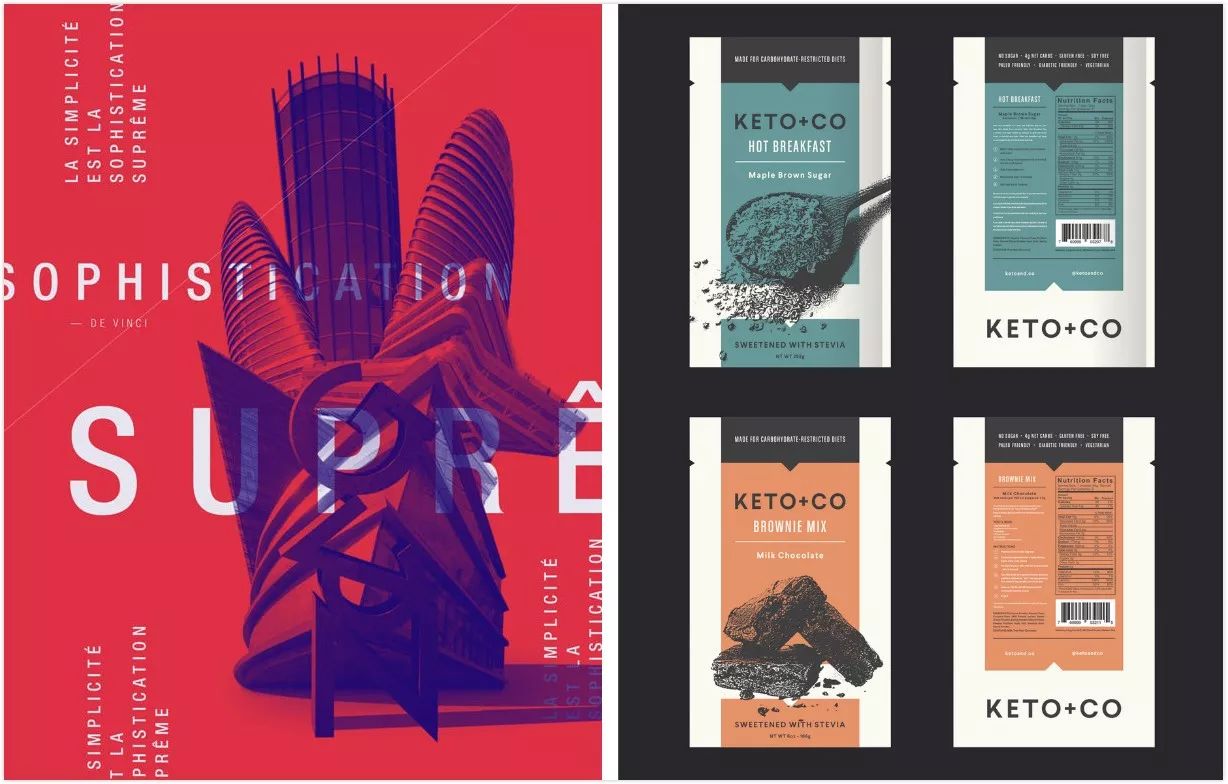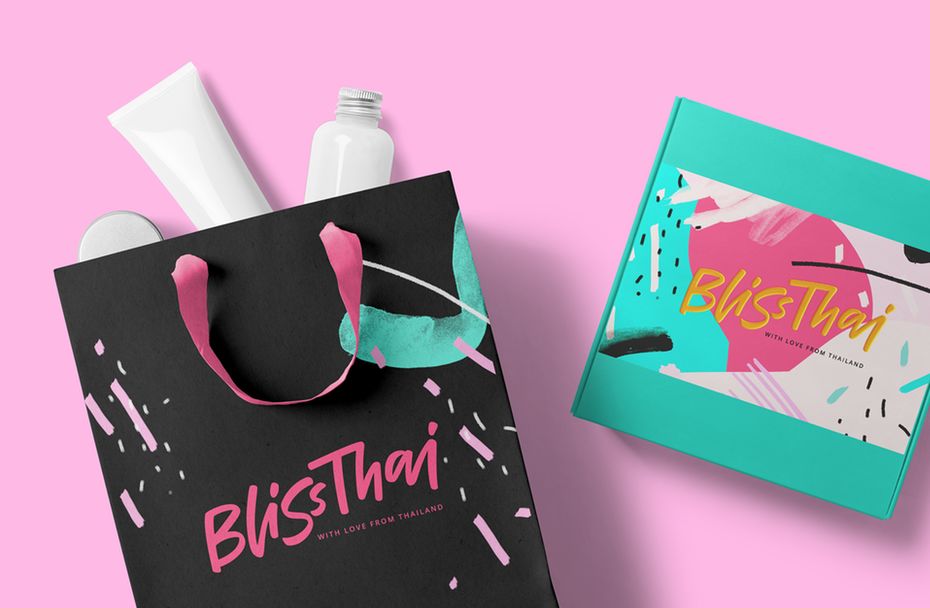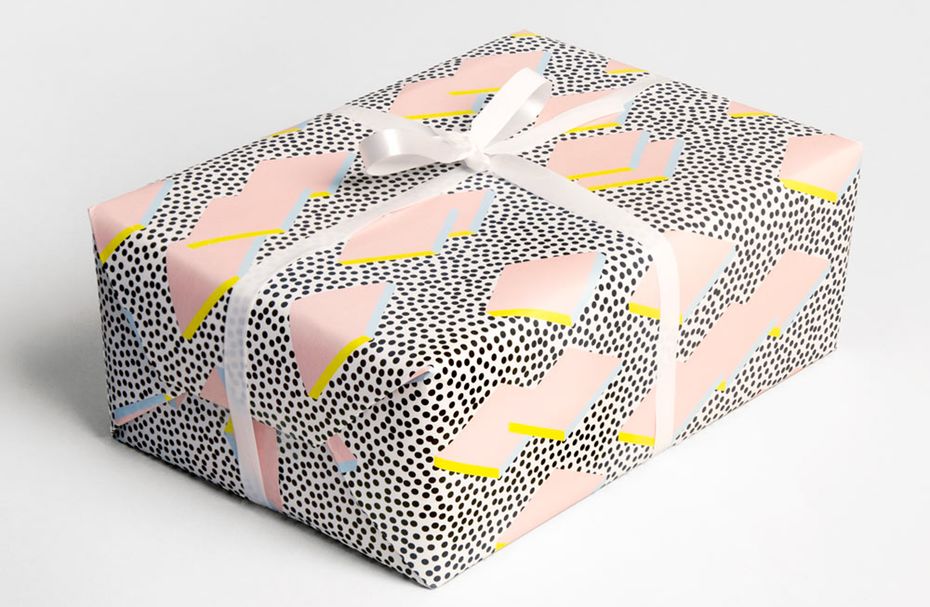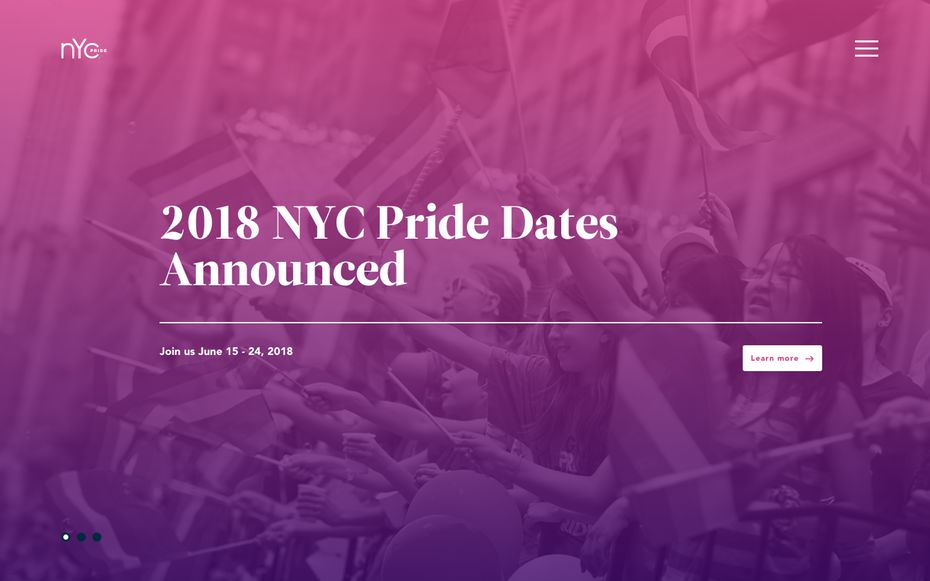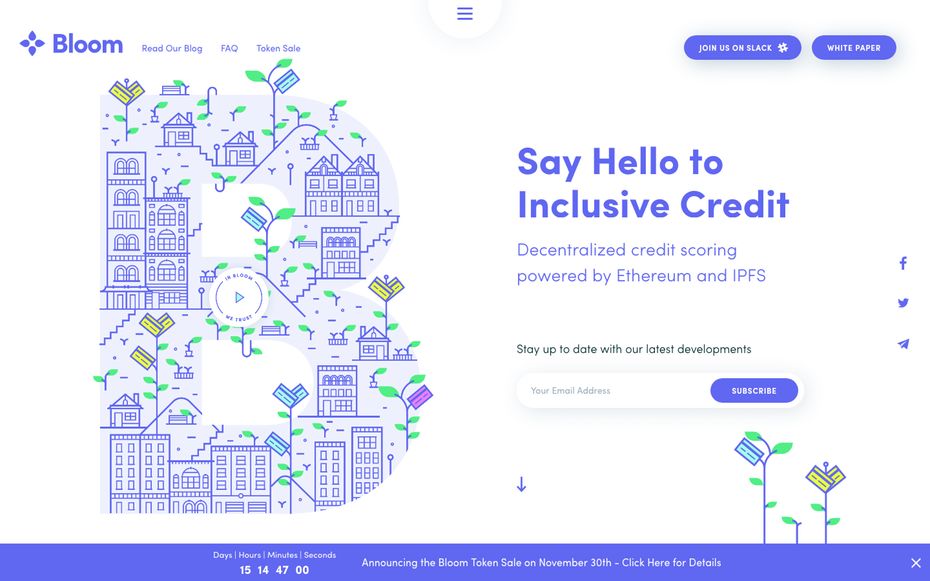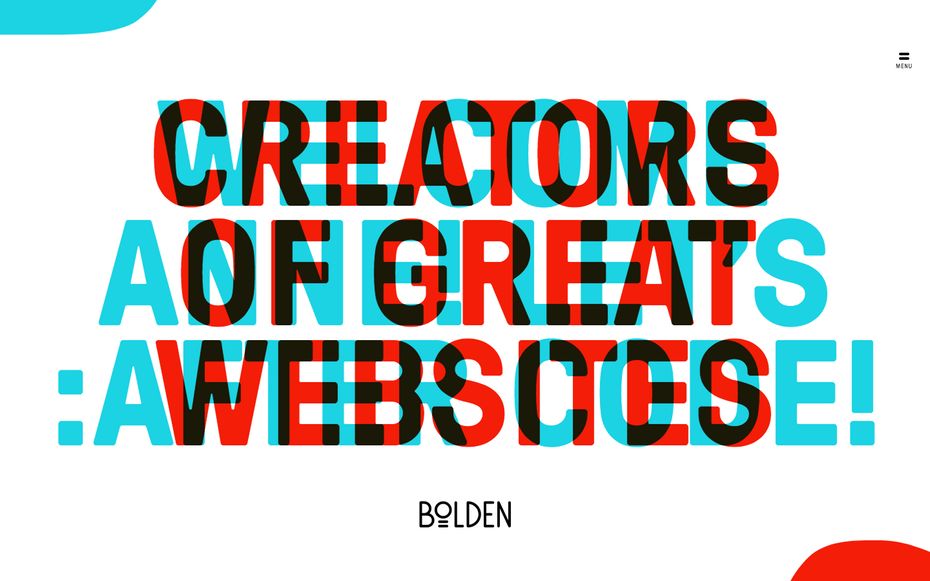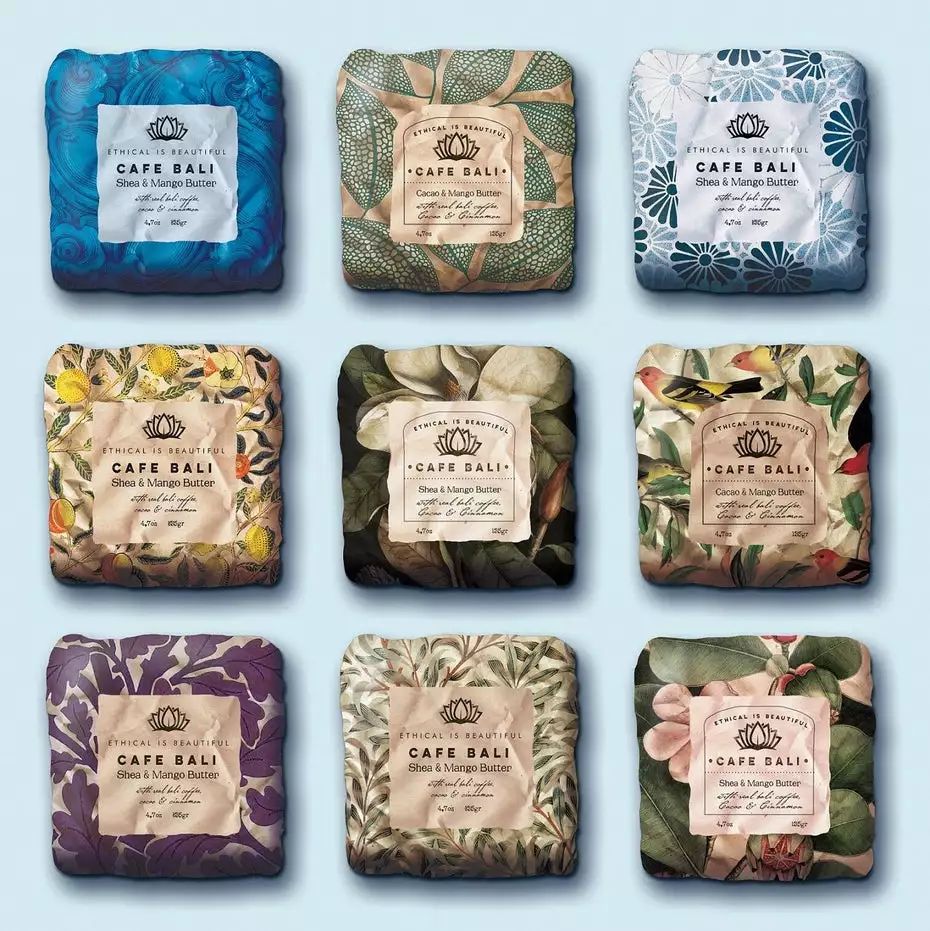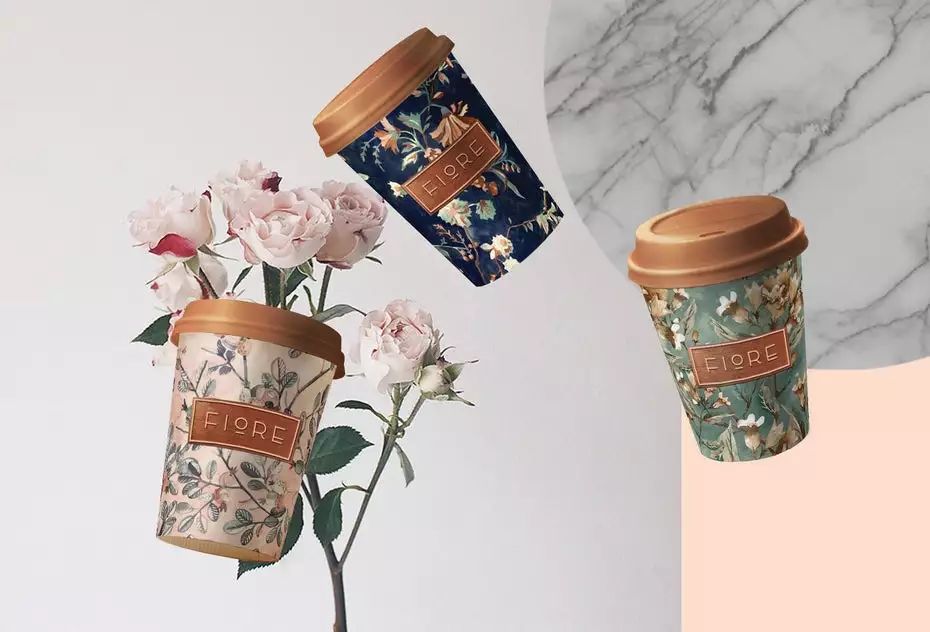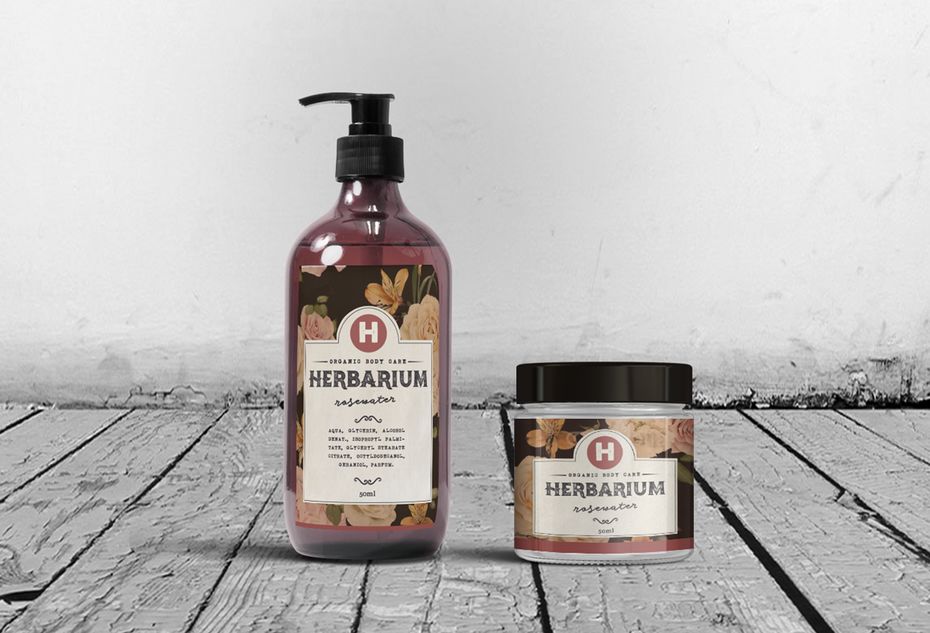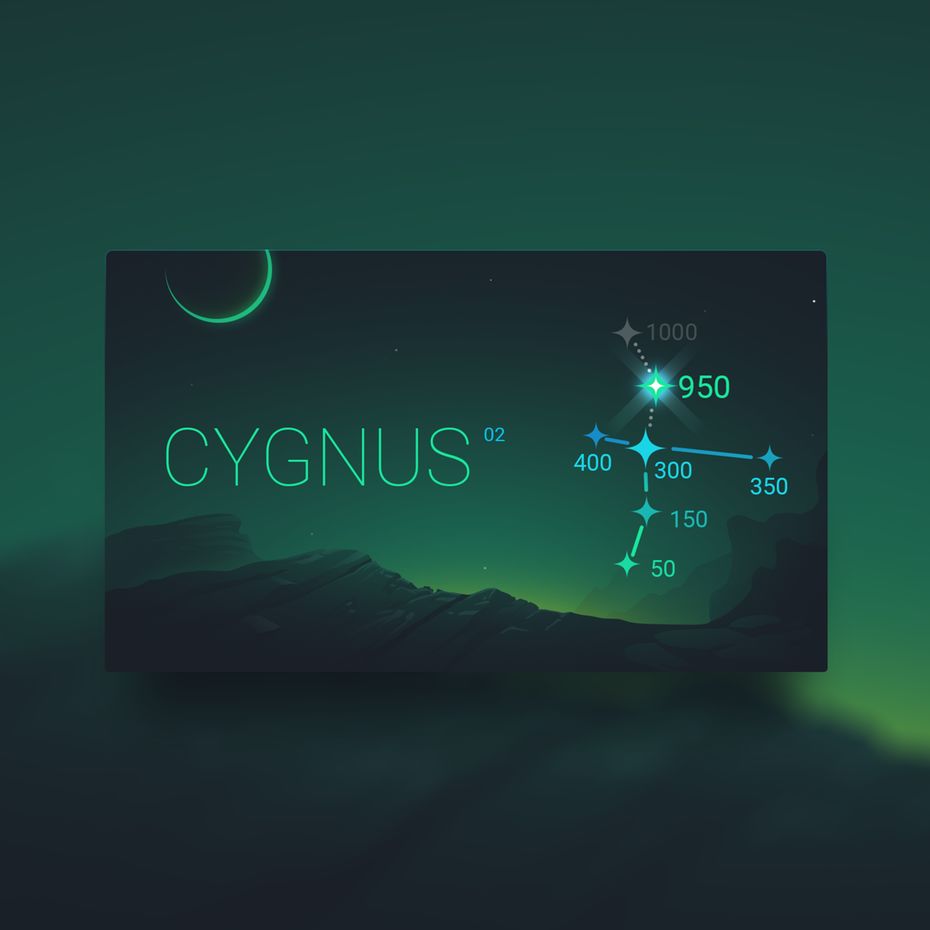
三分钟带你全面掌握2018年十大流行设计趋势
刚刚告别2017年,就迫不及待投身于2018年。前段时间色彩权威机构Pantone发布2018流行色-紫外光色,这或许很酷但还不够全面。
我们为你整理了未来一年的流行设计趋势,来一场视觉感官盛宴。你或许觉得又不是设计师,何必了解这些?但想要在社交圈中建立话语权,成为最有品味审美的那一位,以下三分钟可以帮到你👉
01.
Logo也可以响应式
Responsive Logos
我们都知道响应式网页设计是去年的主流趋势之一,能够适应不同电子设备和屏幕尺寸,产品如果不能适配手机、平板…可就会被用户嫌弃啦。
设计师为了用户在视觉上有最完美舒适的体验费尽心思,即使是小小的Logo也可以响应式。什么?!Logo也可以更改会不会太随意了一点。😳
不过很多品牌已经意识到这一点,在原有品牌标识的基础上推出不同响应式的简化版本。
可口可乐、CHANEL、迪士尼、喜力啤酒
即使简化到只剩下一个元素,我们依然能一眼识别这个品牌。而在未来一年这个趋势将越来越流行,交互设计师Joe Harrison还自发创建“响应式Logo”的项目,探索世界上一些知名品牌该如何简化标识。
skype、Google
02.
渐变色
Gradients
渐变色在去年风靡设计圈,我们在网站的各个页面、控件、标题、背景色甚至ppt中都能看到,如果ppt中不来点渐变可一点都不酷。
“呐,我想要这种感觉~”
平面视觉设计正在向一个新的方向过渡,渐变色“光与影”的运用使其开始向立体多维转变,进入“半扁平化设计”或者说“扁平化2.0”时代。比如在UI设计、品牌标识、背景色、插画设计等各个领域,渐变色都很吃得开。
充满活力的渐变色
生动的色彩过渡,结合插画和阴影来体现
当我们提到渐变色时,通常也是指“色彩过渡”,在平面设计美学中体现的充满活力、光滑平坦的色彩应用。
Logo设计、APP静态页面
03.
阴影深度
More depths
阴影的运用在2018年将正式回归~在设计中多用于背景辅助,毕竟拟物化设计渐渐退出时代的前沿,我们依然钟爱极简主义的风格,阴影增加了更多的细节。
卡片设计 by boorykin
可不要小看阴影的运用,阴影深度帮助用户确定视觉层次结构。比如可以在哪里输入文字、哪里点击按钮…一目了然,相当给力。
2017年Google Material Design重新引入真实阴影增强UI设计,设计师们当然是紧随潮流,抱紧Google大腿,在平面设计中阴影的运用使其更具空间立体感。
阴影可能是大片面积、多色彩、微妙的…在不同场景中灵活运用。
大而柔和的阴影有助于提升网站设计的层次性
处女座,哦不纯粹主义者可能不喜欢它。但阴影深度已经证明可以通过提高可用性和简洁性来适应平面设计的不断变化,这难道就是传说中的以不变应万变?
未来一年,这将成为“半扁平化设计”的基本特性。在过去我们已经看到阴影深度在图标、插画、网页、APP设计甚至印刷产品中的延展运用👏
微妙的阴影运用帮助UI界面的弹出
04.
大胆的双色调
Dashing duotones
双色调其实在传统印刷技术中应用很广泛啦,听起来是不是毫无新意,然而在数字媒体时代被赋予了新的生命。比如双色调、三色调甚至“假双色调”,先进的技术让我们看到更多可能性。
Spotify使用双色调图像进行品牌和封面艺术
全球最大的音乐服务平台Spotify在网站和APP中运用双色调图像,重返主流设计。
这种看起来超炫的技术,在有限的调色板中创建色彩丰富的图像,为图片增加了独特的设计元素,非常适合“半扁平化设计”。
05.
复古八九十年代调色板和图案
Palettes&patterns by the 80's&90's
极乐泰国受80年代灵感设计的品牌形象
80年代风格的包装设计
从粉嫩的粉红色到数字色彩,八九十年代流行的配色方案将再次流行。而被这个时代风格所激发的灵感,比如抽象、几何图案元素…期待它们也将成为主流。
Redux品牌标识设计
80、90后日益成为消费群体主力军,对于各大品牌而言我们的需求太重要了。而这一复古色彩趋势的再次流行将为80、90后带来视觉上的强烈冲击和怀旧感,还不赶紧用起来😝
时髦插画是复古与平面的有趣结合;几何图案和霓虹灯色彩的结合
大胆的配色和爵士风格的图案让名片脱颖而出
06.
微交互:动画&GIFs
Movement:animation&GIFs
微交互可以帮到你~为用户创造意想不到的惊喜,让他们时刻想要参与进来,毫无刻意的痕迹。是不是很酷?微交互可以说是迄今为止用户体验最重要的设计趋势之一。
微交互无处不在,当我们刷微博、滑动页面、跳转至下一首歌时,都是与微交互接触的时刻。这些细节让用户觉得他们的操作得到正面的反馈。
当涉及到大的动画制作时,GIFs和SVGs是非常有效的工具为用户生产优质的内容。
在广告、插画、图标、Logo中灵活运用这一趋势,动态GIF的Logo已经被广泛使用,看起来更具年轻化和吸引力。
如果觉得以上还不够爆炸,cinemagraph正在强势回归!利用静态照片中神奇的动态技术。想象一下在静态风景中迎风吹动的树叶,这种动静结合的极端对比有种超脱现实的美感。2018年在社交媒体广告中系列中绝对大受宠爱。
07.
大胆的排版(衬线体重返屏幕)
Bold typography(serifs return to screen!)
我们常说细节很重要,不过在2018年你会发现排版越来越大。设计师毫不手软地选择艺术效果、超大的字体和标题,效果却意外地好,让用户将目光聚焦在最重要的信息上。
Helvetica风格的无衬线字体无处不在,尽管2018年还是一样流行,但我们也该玩些新花样啦。新的一年期待设计师运用更多不同风格的字体。
比如衬线体的再度流行,尤其与无衬线体配合出现的时候,在界面设计上越来越多的设计师喜欢运用~可以预感,2018年无衬线体终于不用躲在衬线体背后,开始有更大的话语权。
我们在一些印刷品上看到的趋势将在线上找到它们的应用方式。比如艺术版式、更有创意的布局、图像的位置、以及字间距的变化等。
08.
自定义图形艺术和插画
Custom graphic art and illustration
不论是那些异想天开、实用的还是纯粹的艺术,在新的一年,定制图形艺术和插画的需求将持续增长。
那些经典的绘画、书法、艺术排版、摄影和插画…用得太多感到有些腻味,包括现代经典平面设计技术,例如双色调和双重曝光,在数字媒体技术快速发展的时代,同质化成为一个很大的问题。
傻傻分不清😅
定制图形艺术和插画有助于创建全新的视觉语言,为品牌增加独有的个性。
2018年,不论是设计师还是需求方都将开始重新运用这些未被充分利用的资产,创造出真正的创意,带来全新的视觉艺术体验。
09.
真正的摄影
Authentic photography
真正的摄影图片能让用户体会到真实的情感和故事,表达创作者的真实心境。
90年代的广告特别偏爱未经过滤镜和处理的摄影作品,自然而生动。相信在接下来一年这将再次成为主流,有温度的作品总是能让人心生好感。
现实生活中对摄影的需求将大幅增长,尤其是品牌为了加强与用户之间的联结,优秀的摄影作品具备极强的感染力。
设计师也在试图摆脱那些俗气乏味的摄影作品,而越来越多有才华的摄影师能够满足这些巨大的需求,提供优质甚至免费的摄影资源,为他们打call!
10.
复古老式的风格
Highly-detailed vintage
繁华复古的风格有种永恒不褪色的美丽。虽然我们都爱极简主义的性冷淡风,但这一点都不妨碍我们欣赏这种复古老式的设计。用精致的插图、标志细节赋予产品更深次的个性。
尤其是一些知名品牌早已发现这种经典的设计美学为他们带来独特而精致的风格。
当然啦,不是所有领域都适合这一设计趋势。不过在食品和饮料行业尤其是葡萄酒等酒类品牌,利用这一复古老式的设计风格,特别受用户的喜爱,销量都是杠杠的!
给用户带来纯手工制作、简单干净的视觉感受。
准备好了吗?2018新的一年,我们即将看到图形艺术的复兴、八九十年代风格的回归、微交互的全面应用、大胆的排版…让它们来激发与众不同的设计创造力,让每一点微小的改变汇聚成涓涓细流,使产品具备长盛不衰的生命力。